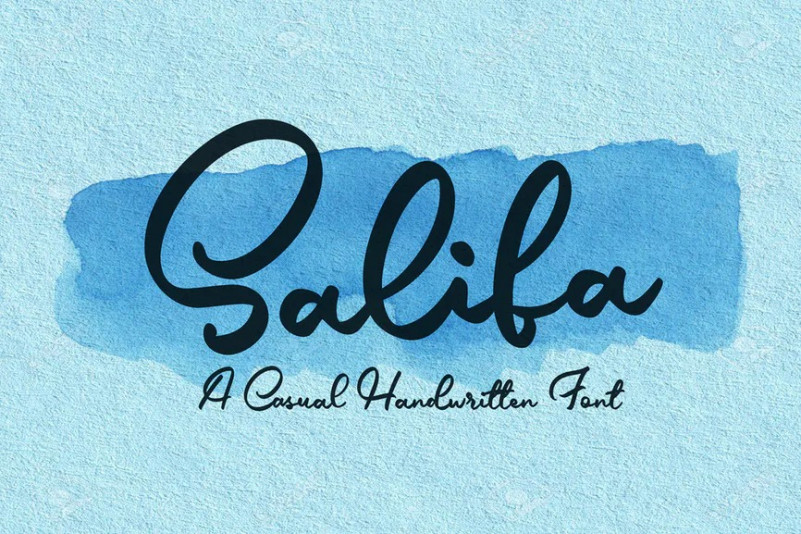
Salifa Font
Salifa Font est une police manuscrite qui est parfaite pour l’image de marque, les en-têtes de médias sociaux, l’emballage de produits, les invitations de mariage et les cartes et ainsi de suite. Cette police est entièrement dessinée à la main et contient 179 ligatures pour recréer parfaitement l’écriture naturelle.